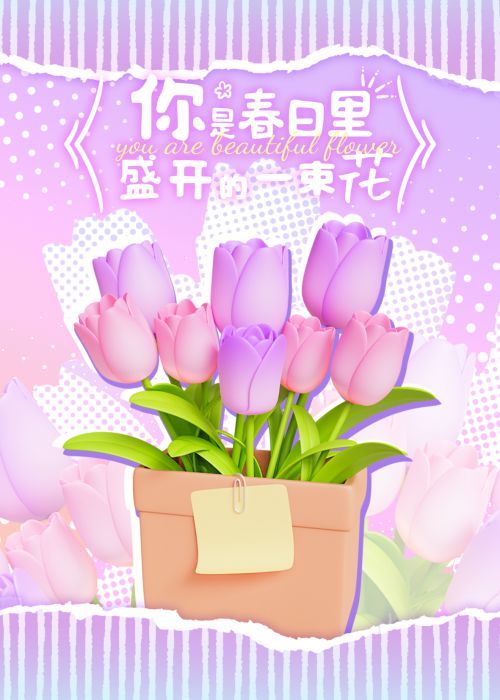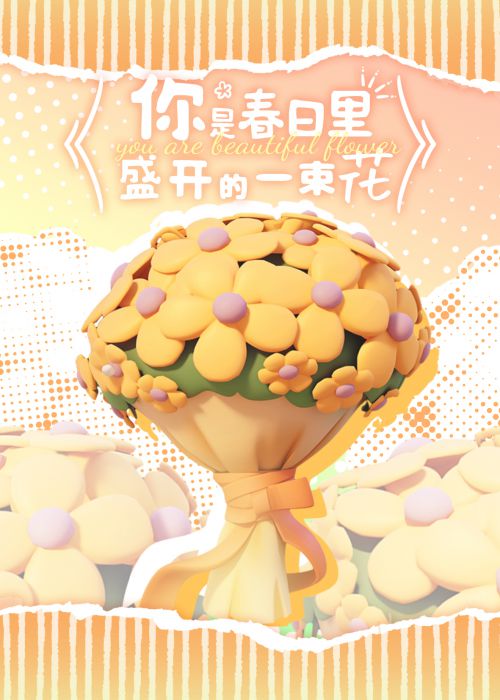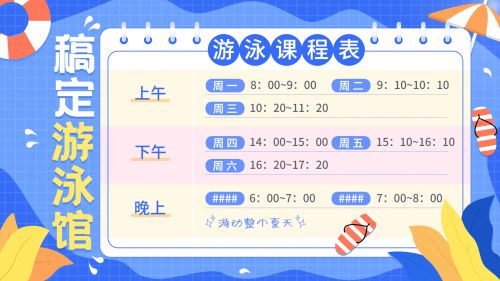
阿朱泡泡体
阿朱泡泡体是一款充满趣味的创意手写风字体,以独特的视觉设计和可爱气质脱颖而出。字体整体呈扁宽形态,重心居中稳定,中宫宽博的结构让字形舒展大气,既保留手写字体的灵动,又兼具清晰的识别度。 阿朱泡泡体在笔型设计上尤为用心,笔画边缘融入圆润的装饰元素,搭配粗且均匀的线条,呈现出如气泡般饱满可爱的视觉效果。圆头笔画与断开的连接方式,更添几分俏皮感,让每一个字符都像被注入了生命力,适合传递轻松活泼的氛围。作为免费商用字体,阿朱泡泡体广泛适用于海报设计、文创产品、社交媒体配图等场景,无论是儿童主题内容还是年轻化品牌宣传,都能以其独特的亲和力点亮视觉画面。